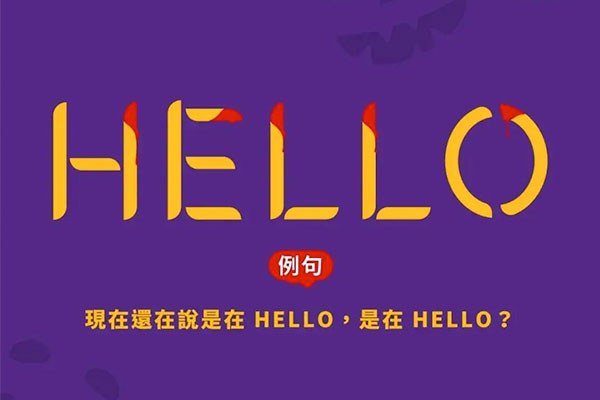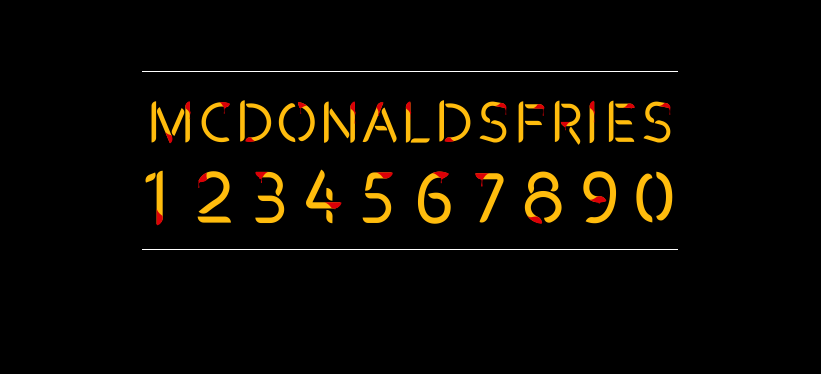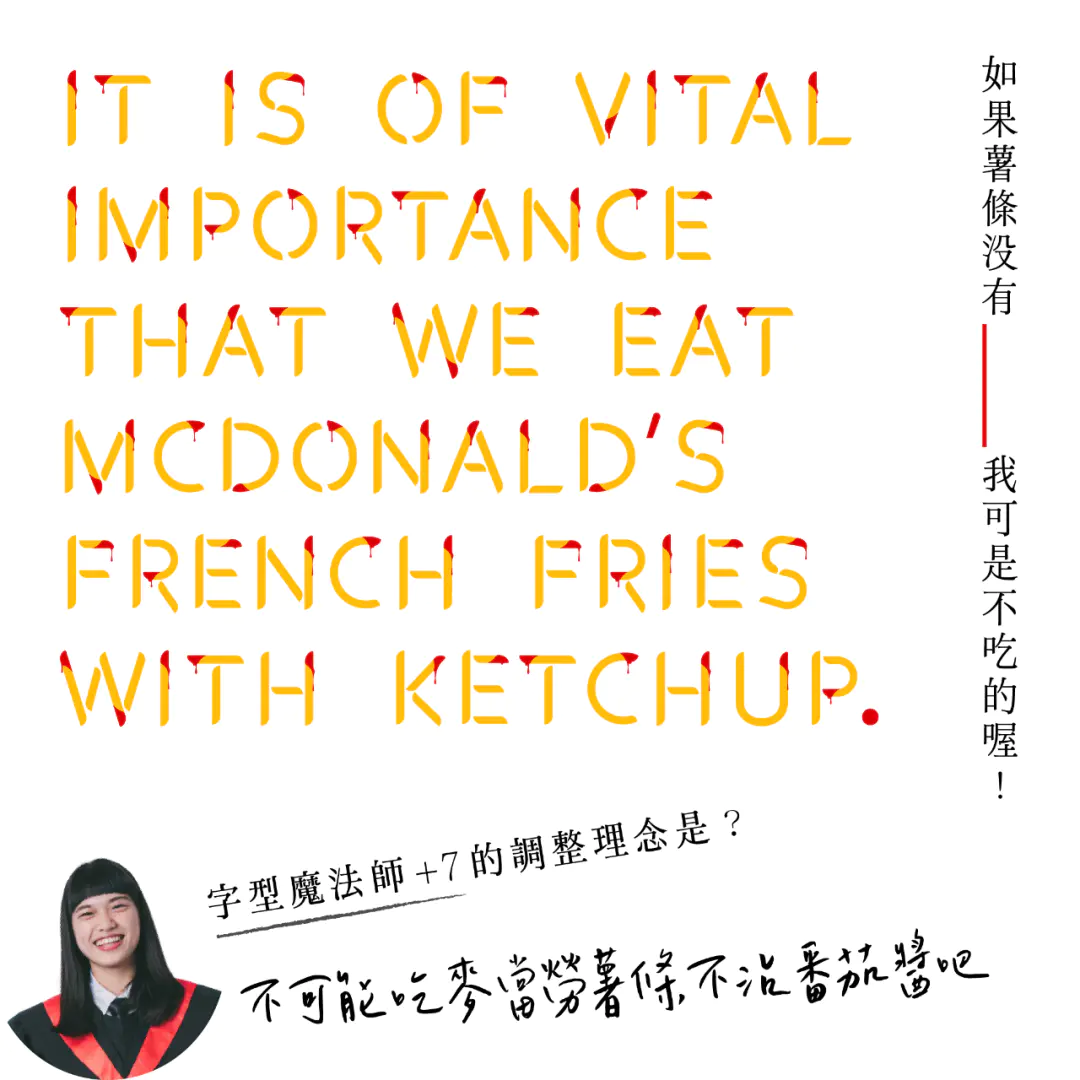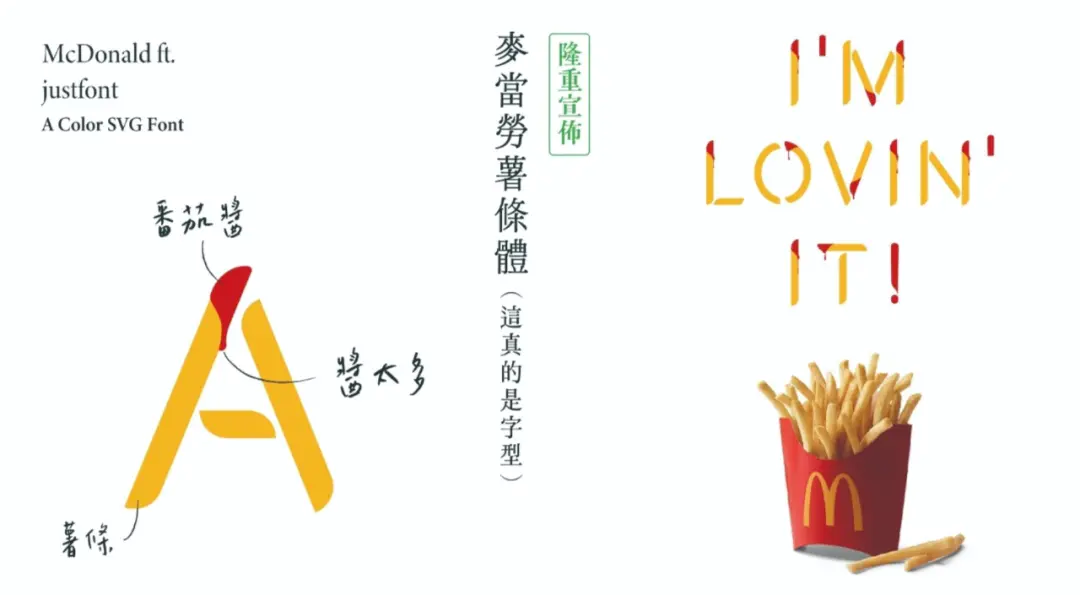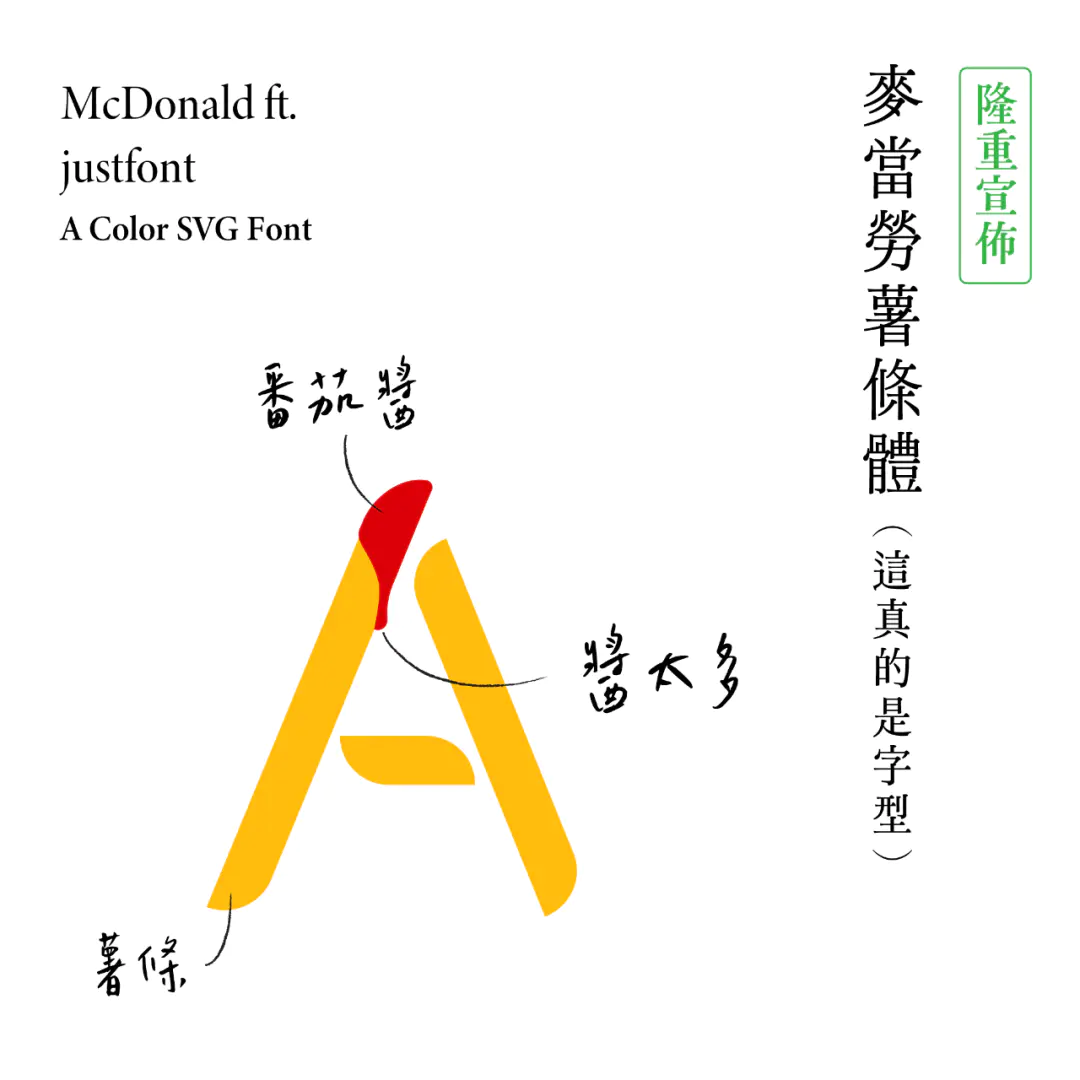
麦当劳薯条体
麦当劳薯条体的字型设计由麦当劳出品,邀请台湾地区字型设计团队justfont 协助字型编码与调整。
26 个英文字母以金黄色薯条为主体,在笔画的开端、末端沾上红色番茄酱点缀;标点符号则完全以番茄酱的红色表示。
薯条体上沾满欲滴的番茄酱,也让人联想到万圣节常有人扮演的吸血鬼,十分应景。